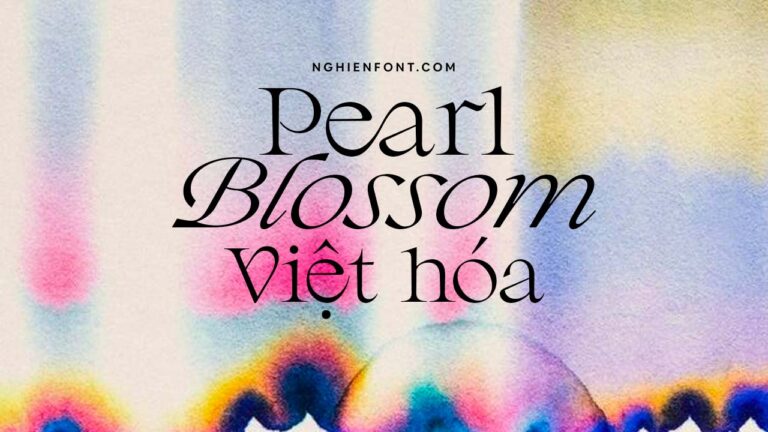
Font việt hóa BHN Pearl Blossom siêu đẹp
Font viet hoa BHN Pearl Blossom
Pearl Blossom là một kiểu chữ serif thanh lịch và hiện đại với phiên bản in nghiêng calligraphic. Cả hai phông chữ đều có phiên bản REGULAR và BOLD.
Pearl Blossom mang đến một cái nhìn hiện đại và rõ ràng cho nhiều thiết kế khác nhau như tiêu đề, logo, trang web, phương tiện truyền thông, thiệp mời, tạp chí…
Pearl Blossom có 61 Ligatures (chữ ghép) và 19 Alternates (chữ thay thế).
Font BHN Pearl Blossom việt hóa Preview
Font việt hóa BHN Pearl Blossom pic1
Font việt hóa BHN Pearl Blossom pic2
Font việt hóa BHN Pearl Blossom pic3